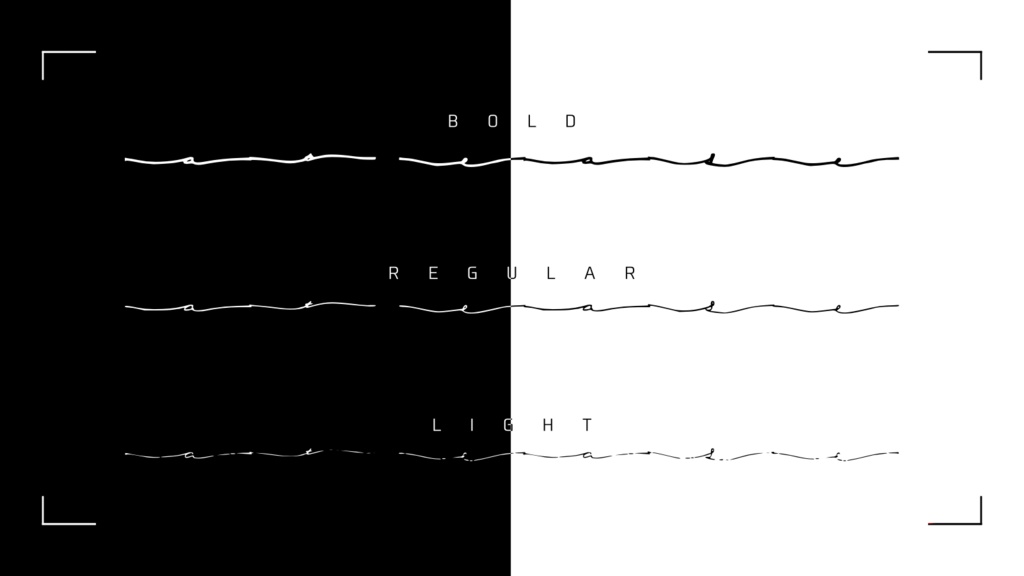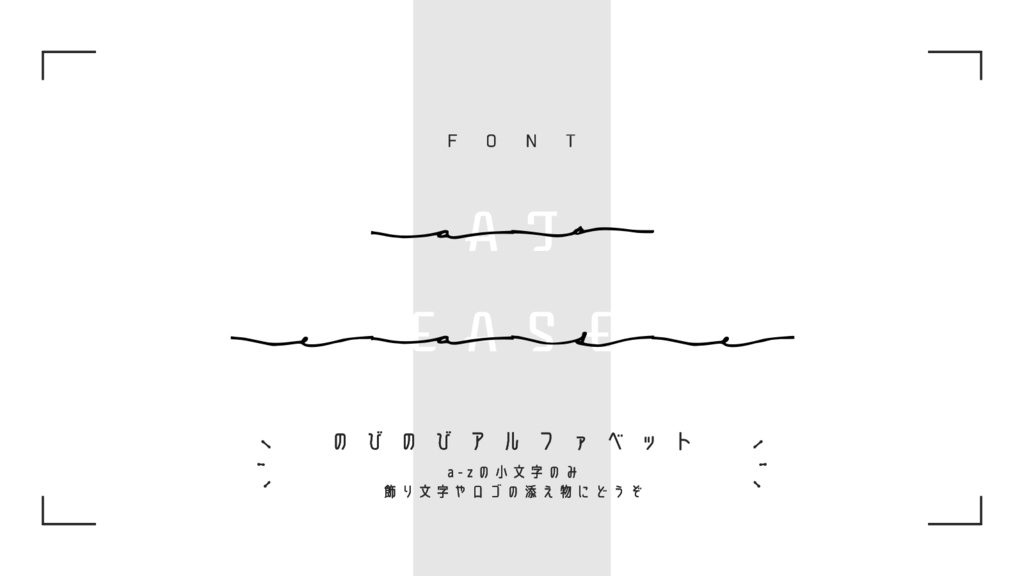
フォント素材「at ease」
手グセで書き散らすしているアルファベットをフォント化したものです 当フォント主体でなく 飾り文字やロゴの添え物などにどうぞ 単品での可読性が低いため 他のフォントなどと組み合わせてお使いいただくと読みやすくなります 収録文字は「a-z」の小文字アルファベット26字のみです light・regular・boldの順に太く lightはかなり掠れ、boldはサインペンのようなタッチになっております (1枚目トレイラーはbold/文字間隔狭め) ─────────────── (20230104) 一度フォントを作ってみたかったので なんとかなってよかったー!ということで 少しの間ALLファイルを¥1,000→¥500セールしてます